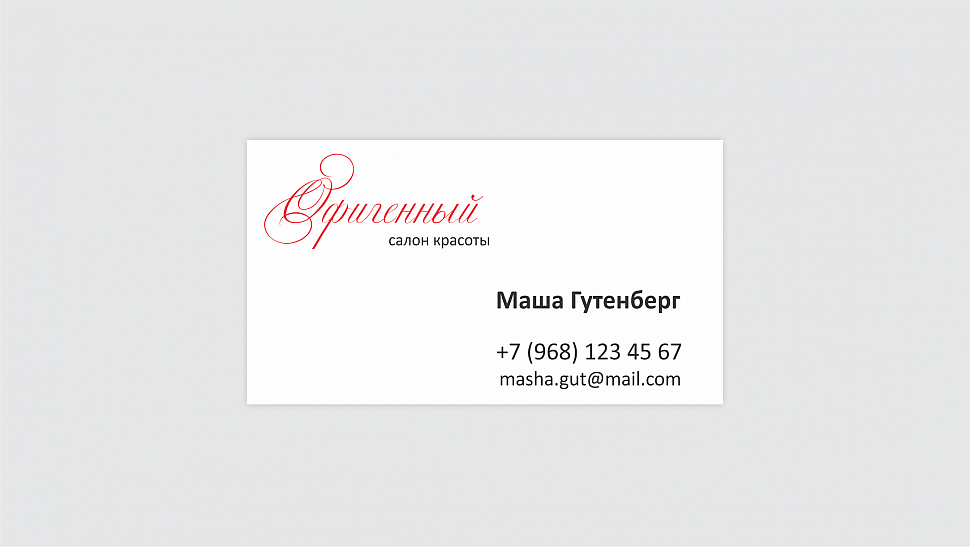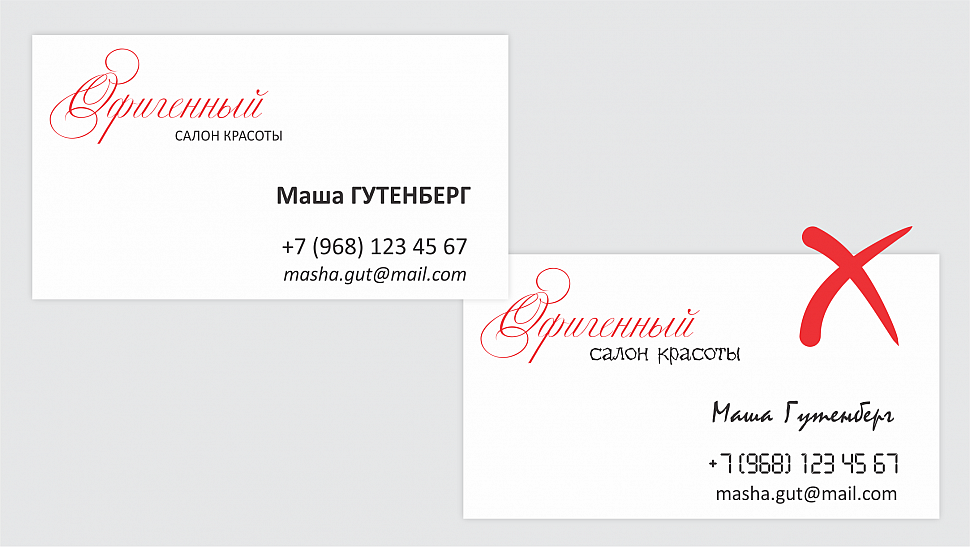
Какой самый лучший шрифт для визитной карточки?
Жаль, но такого шрифта пока ещё не изобрели… Что же делать? Шрифтов – миллионы, а нужный никак не получается найти! Именно поэтому наша типография сделала подборку из самых актуальных шрифтов для визитных карточек на 2019 год, а также полезные советы для того, чтобы выбрать лучший шрифт.
Почему не существует идеального варианта для всех?
Причин много. Разные вкусы, желания и цели. Невозможно соединить все пожелания людей в один шрифт. Для выполнения главной функции визитной карточки (а именно привлечь внимание и сделать уникальной) используются не просто разные шрифта, а в всевозможные комбинации этих шрифтов.
Что нужно знать при выборе шрифта?
- Во-первых, визитка очень мала, поэтому нужно выбирать читабельный, понятный шрифт.
- Во-вторых, нужно выбрать правильный шрифт под материал, который Вы хотите использовать.
Для матовой бумаги советуем более нежные и гладкие шрифты. Для простой – более сдержанные и строгие. - В-третьих, обращайте внимание на свою специфику работы. Если Вы занимаетесь маникюром красиво бы смотрелся шрифт Brusher Cyrillic, Bryndan Write, Caveat и другие подобного плана (резкие, словно быстрый взмах кистью). Для строителей, подрядчиков, сантехников такие шрифты будут явно странными и скорее запутают человека – Вам нужны ровные, строгие и прямые (Bebas Neue Cyrillic, Capture Smallz Clean и прочее).
Подборка полезных 5 шрифтов для визитки на 2019 год
Neuton
Neuton — прекрасный вариант для любителей шрифтов с засечками.
Чем-то напоминает привычный многим, кто когда-то открывал Ворд, шрифт Times. Он компактный в ширину, поэтому можно сэкономить место и он будет хорошо смотреться на экране. Подходит для классической или современной визитки.
Ambarella
Занимаетесь ручной работой? Шьёте, вяжите, создайте дизайн одежды? Гарнитура Ambarella покажет и расскажет это на Вашей визитке. Для настоящих ценителей легкости и красоты. Лучше всего выглядит на матовой бумаге.
Ubuntu
Гарнитура часто используется представителями технологической индустрии, программистами и инженерами. Один из новых шрифтов, представленный в 2010 году.
Alcubierre
Alcubierre — прекрасный вариант для того, чтобы передать легкость и воздушность в дизайне визитки. Аккуратные и мягкие формы, легкие линии делают её уникальной. Помогают людям ощутить «глоток свежего воздуха», глядя на Ваши визитки.![]()
Milkshake
Молодежная, сочная и вкусная гарнитура, которая идеально подходит для визитки и личного резюме. Часто её выбирают кофейни, кондитерские и молодые предприниматели. Буквы жирные и толстые – их легко прочитать и составить ассоциацию с тем же густым и жирным молоком. Похоже на текст, написанный чернильной ручкой. Весьма универсален.
Как выбрать лучший шрифт для визитки
Представьте себе сцену: вы открываете текстовый документ и вводите название своей компании.
На белом фоне оно выглядит мелко, поэтому вы увеличиваете размер до 96. Вы снова произносите название вслух, чтобы услышать, как оно звучит. Это лучший вариант из длинного списка, написанного в вашей записной книжке. Затем вы исследуете меню шрифтов, чтобы увидеть, как оно выглядит в разных стилях букв.
Прежде чем вы это заметите, пройдёт двадцать минут, и вы станете более нерешительным, чем раньше.
Очень. Много. Вариантов.
Ваш бизнес современный и минималистичный или традиционный и элегантный?
Есть тысячи стилей, из которых можно выбирать. Выбор типографского стиля, который будет определять ваш бизнес на следующие несколько лет, представляет собой непростую задачу. Мы надеемся, что эта статья укажет вам правильное направление.
Итак, что такое шрифт?
Шрифт — это набор букв и цифр, акцентов и символов, созданных для единого дизайна. Любые варианты одного и того же дизайна, например, полужирный, обычный или курсив, называются «семейством шрифтов».
Шрифты, которые вы используете на своих визитных карточках, выполняют две основные функции, привлекают внимание и их легко читать.
Имея это в виду, читайте дальше, чтобы узнать больше о типах шрифтов, о том, как комбинировать разные стили и какой размер вы должны сделать для текста на своих визитных карточках.
Типы шрифтов
Что такое шрифт без засечек?
В типографике буквы без засечек не имеют декоративных линий, называемых «засечками», в конце штрихов. Шрифты без засечек также имеют меньше вариаций ширины линии, чем шрифты с засечками (подробнее о них через секунду). В печатной продукции шрифт без засечек лучше всего подходит для названий компаний, заголовков или вывески, поскольку их легко прочитать с первого взгляда. Это также хороший выбор, если вы хотите передать простоту, современность или минимализм.
Шрифты без засечек часто используются для цифрового отображения текста. На дисплеях с низким разрешением мелкие детали, такие как засечки, могут исчезать или казаться слишком большими в зависимости от шрифта.
И на всякий случай, если вам интересно, этот термин происходит от французского слова sans, означающего «без», а «serif», как полагают, происходит от голландского слова schreef, означающего «линия» или штрих пера.
Что такое шрифт с засечками?
Засечки происходят от резных надписей, которые часто встречаются на исторических зданиях, мостах и надгробиях. Эта историческая ассоциация делает буквы с засечками идеальными, если вы хотите создать устоявшийся и традиционный вид. Шрифты с засечками — это наиболее часто используемый стиль в длинных рукописях, книгах, газетах и большинстве журналов. Это связано с традициями, воспринимаемой удобочитаемостью и низким качеством бумаги в прошлом, которые делали оптимальным печать с использованием букв с засечками.
Однако дискуссия о читабельности — спорный вопрос. Один лагерь утверждает, что читаемость и скорость чтения длинных отрывков текста улучшаются, поскольку шрифты с засечками помогают взгляду перемещаться по строке.
Другой лагерь оспаривает это, считая, что буквенный стиль, который мы чаще всего читаем (текст с засечками), легче всего читать.
Помните, что, если вы хотите добавить рельефный глянец к шрифту с засечками на своей визитной карточке, рекомендуется добавлять его только в большое текстовое поле, такое как название вашей компании.
Где использовать рукописные шрифты
Рукописные шрифты — это шрифты, которые передают человеческие прикосновения, такие как плавные курсивные штрихи и соединенные рукописные надписи. Рукописные шрифты отлично подходят для приглашений, поздравительных открыток, заголовков или очень коротких выразительных текстов с личным сообщением. Классические плавные рукописные шрифты создают элегантный вид, а округлые формы создают ощущение удовольствия. Они могут быть эффективными для привлечения внимания, но позаботьтесь о том, чтобы обеспечить их разборчивость, особенно если вы планируете использовать рукописный шрифт для своих вывесок.
Как комбинировать шрифты на визитке
- Сузьте свой выбор до двух шрифтов для своей визитной карточки
- Попробуйте сочетать шрифт script или serif с шрифтом sans-serif
- Создайте визуальную иерархию, решив, какая информация наиболее важна, например, ваша компания или полное имя. Затем определите, какая информация может отображаться в меньшем размере ниже.
- Не обязательно полагаться на размер текста, чтобы добиться визуальной иерархии. Попробуйте использовать жирный шрифт для заметного текста и светлый оттенок для менее заметных текстовых полей.
- Используйте на визитной карточке не более трех размеров шрифта. Два — идеальный вариант. Создайте контраст между текстом и фоном в своем дизайне.
Делайте так, чтобы каждое текстовое поле выделялось. В случае сомнений всегда выделяется черный или темно-серый текст на белом или желтом фоне. - Избегайте сочетания похожих шрифтов. Постарайтесь создать некоторый контраст между названием вашей компании и полем контактных данных.
Размеры шрифта визитной карточки: лучшие практики
В типографике размер пункта (pt) — это стандартная единица измерения, используемая для измерения букв в дизайне. Для заметных текстовых полей визитной карточки, таких как ваша компания или полное имя, размер шрифта может быть от 10 до 16 пунктов в зависимости от того, сколько места у вас доступно. Эти размеры должны отличать основные текстовые поля (наиболее заметные) и второстепенные (менее заметные).
Размер ваших менее заметных текстовых полей, таких как название должности, адрес электронной почты, Интернет, адрес и номер телефона, очень важен с точки зрения видимости и разборчивости. Минимальный размер, который вы должны использовать на наших визитных карточках, — 8 пунктов, но имейте в виду, что некоторые шрифты могут казаться меньше других, даже если оба шрифта имеют одинаковый размер.
Будьте осторожны с рукописными шрифтами и некоторыми засечками небольшого размера. Если вам нужно добавить мелкий шрифт, используйте шрифт без засечек для оптимальной разборчивости.
Помните, что прежде всего текст на визитных карточках должен быть легко читаемым. Как только вы найдете шрифт, который легко читается с первого взгляда, вы можете начать экспериментировать с цветовыми сочетаниями, чтобы выделить свой дизайн.
Визитки — цвет и шрифт | Новости
Создавая визитку, нелишне будет учесть два таких немаловажных аспекта, как цвет и шрифт. Рассмотрим их более подробно:
1) Цвет визитки. Поскольку визитная карточка обладает сравнительно небольшими размерами и при этом предлагает солидный объем информации, то крайне желательно, чтобы визитка представляла собой текст темного цвета на светлом фоне. Если задействуется так называемая выворотка (светлый текст сочетается с темным фоном), то это приводит к уменьшению общего количества текста примерно на треть.
Оформление визитки должно быть максимально строгим, без вычурных завитушек и рамок (это касается в первую очередь деловых визиток; для людей творческих профессий, разумеется, допустимы самые разные варианты). В соответствии с нормами этикета лучше всего заказывать визитки на качественной бумаге высокого качества (очень хорошо, если это дизайнерская коллекция). Не рекомендуется делать поверхность глянцевой – дело в том, что на визитках очень часто оставляют уточняющие пометки, а в этом случае это будет попросту невозможно. В соответствии с нормами этикета подразумевается использование белых, голубых, розовых цветов для фона и черного либо синего цвета для шрифта.
2) Шрифт визитки. Как таковых жестких рекомендаций, связанных со шрифтом, нет – здесь очень многое зависит от сферы деятельности фирмы. В частности, представителям компании, которая предлагает художественную ковку, подойдет готический шрифт с вензелями, подчеркивающий высокое качество изделий ручную работу, их ориентацию на древность и античность.
Напротив, если фирма предлагает современные товары (например, ноутбуки последнего поколения), то здесь будут уместный рубленые шрифты без засечек. Также можно изменять начертание шрифта – например, с помощью жирного шрифта делать акценты на важной информации, а курсивом или тонким шрифтом подчеркивать ювелирное мастерство, сложность работы и изящность товара. Впрочем, не следует забывать об основном правиле – шрифт обязательно должен хорошо читаться. Если визитка читается плохо, то она очень быстро окажется в мусорной корзине. При помощи шрифтов можно правильно расставить акценты (например, выделить несколько большим шрифтом фамилию, имя и отчество владельца). Акценты в визитке, помимо размера шрифта, могут достигаться при помощи форматирования, а также с использованием цветовых наложений на определенные текстовые фрагменты.
Заказать визитки в типографии «Псковское возрождение».
Как должна выглядеть визитка: материал, шрифт, цвет
Визитка — это доступный и простой в изготовлении рекламный материал.
С ее помощью можно распространить информацию о компании или же о конкретном специалисте. Визитные карточки заказывают не только крупные фирмы, но частные мастера, которые работают на себя и оказывают различные услуги (слесари, электрики, программисты и другие).
Такие изделия изготавливается в форме небольшой карточки, которая содержит контактные данные. Важно понять, как должна выглядеть визитка и каким цветом ее оформлять, чтобы она привлекла внимание потенциальных клиентов.
Зачем вам нужны визитки?
Визитки можно использовать для:
Повышения своего статуса в глазах клиента, бизнес-партнера или собеседника.
Рекламы. Изделия хорошо сочетаются с сарафанным радио, так как их можно передавать другим, советуя конкретного специалиста или компанию. Чтобы ваши клиенты с легкостью делились вашими визитными карточками со своими знакомыми, оставляйте им по 2-3 штуки, а не по одной.
Передачи контактных данных. Обычно на карточке указывается номер телефона, электронная почта, контакты в социальных сетях и адрес.
Презентации своих услуг. Можно кратко описать, чем вы занимаетесь.
В зависимости от сферы и условий работы визитки можно использовать по-разному. Они позволяют с минимальными затратами распространить информацию о вас и вашей компании.
Какой должна быть визитка
Почему одна реклама работает, а вторая — никак не способствует росту продаж? Потому что не все маркетинговые стратегии эффективны. Чтобы визитка работала на пользу вашего предприятия, она должна быть односторонней, качественной, стандартной по размеру, лаконичной и легкой в восприятии. Почему именно такие визитки работают лучше других? Об этом поговорим далее.
Двухсторонняя или односторонняя?
Не нужно размещать слишком много информации на небольшом кусочке бумаге.
Это перегружает визитную карточку и мешает восприятию информации. К тому же на односторонних изделиях можно делать заметки с обратной стороны. Потенциальный клиент может записать там время встречи или другие данные, которые будут для него полезными.
Иногда вторая сторона используется для печати информации на иностранном языке: так делать не нужно. Чтобы сделать лучшую визитку для иностранного клиента, нужно заказать небольшой тираж полиграфической продукции на нужном языке.
Размер
Размер должен быть таким, чтобы карточка легко помещалась в кошелек, визитницу или в бизнес-холдер. Стандартный размер такой полиграфической продукции — 90 х 50 или 85 х 55 мм.
Другие размеры и необычные формы позволяют реализовывать нестандартный дизайн, но с использованием таких визиток могут возникнуть проблемы. Если они не будут помещаться в портмоне, они будут лежать без дела и очень быстро потеряются.
Стандартные прямоугольные визитки работают лучше, чем другие карточки.
Выбор материала
Материал, на который наносится текст и логотип, должен быть плотным. Если карточка будет сделана из тонкой бумаги, она быстро порвется и помнется. Бумага с тиснением — не самый лучший вариант, так как на ней неудобно делать пометки. Разные декоративные элементы (глянец, тиснение и прочее) лучше всего использовать для тех изделий, которые раздаются как рекламные листовки.
Чаще всего для изготовления визиток используется:
На такой материал можно наносить разные оттенки с хорошей цветопередачей и реализовывать необычные идеи с градиентом, линиями и другими элементами. Также учитывайте, что матовые карточки смотрятся строже и сдержаннее, чем глянцевые.
Какой цвет лучше для визитки
Для фона визитки нужно подобрать такой цвет, который не будет отталкивать, мешать восприятию информации и будет дополнять концепцию бренда. На какие оттенки стоит обратить внимание:
Красный цвет ассоциируется с рекламой, модой и шоу-бизнесом.
Этот оттенок используют компании, которые занимаются организацией праздников, а также фотографы, декораторы и многие другие.
Зеленый часто применяется в образовательной сфере, культуре и искусстве. Этот оттенок выбирают компании, работа которых связана с экологией.
Металлические цвета (белый, серый, серебристый) отлично подходят для финансовых компаний, автосервисов, специалистов по продажам и для организаций, которые занимаются ремонтом техники и электроники.
Черный и голубой оттенки позволяют воплотить многие идеи, связанные с технологией, информацией, туризмом, развлечениями и сферой услуг. Например, в этих цветах можно сделать визитку аквапарка.
Коричневый и желтый оттенки ассоциируются с документами, поэтому их часто используют специалисты, чья деятельность связана со строительством, торговлей и недвижимостью.
Чтобы решить, какого цвета сделать визитку, достаточно рассмотреть несколько вариантов. Дизайнеры рекламно-производственной компании CreativePRO отходят от стандартных решений и предлагают на выбор несколько интересных дизайн-макетов. Каждый дизайн продумывается в индивидуальном порядке.
Выбор шрифта
Чтобы понять, какой шрифт выбрать для визиток, нужно определиться с общей концепцией. Каллиграфические элементы смотрятся красиво, но они плохо влияют на читабельность текста. Универсальное решение — простой шрифт со средним межбуквенным интервалом.
Также шрифты для визиток бывают:
рукописными — их не всегда легко разобрать, поэтому стоит использовать только там, где они будут уместными;
художественными — авторские решения для творческих компаний;
с засечками — короткими перпендикулярными штрихами на буквах;
с тонкими буквами;
с широкими элементами букв.
Специалисты CreativePRO предложат вам несколько вариантов шрифтов на выбор, учитывая стиль дизайн-макета. Надписи должны быть читабельными и не громоздкими. Наши дизайнеры знают, как эффективнее всего презентовать информацию о ваших услугах на визитке.
Какая информация должна быть на визитке
На визитке обязательно должны быть указаны имя и фамилия специалиста, его контакты и контакты фирмы, в которой он работает. Сложные рисунки и ненужная информация могут сместить акцент на себя, усложнив восприятие. Также можно добавить краткий перечень основных услуг. Если у фирмы есть логотип, его обязательно стоит использовать при создании дизайн-макета визитной карточки.
Не перегружайте изделия лишней информацией, если вы работаете в разных сферах. Лучше закажите в CreativePRO несколько вариантов карточек для разных ситуаций. Такое решение подходит для тех фирм, которые специализируются на предоставлении различных услуг.
Например, если вы преподаете английский, а в свободное время делаете торты на заказ, вам стоит сделать две визитные карточки.
Выбирать дизайн для визиток нужно внимательно, учитывая все тонкости их дальнейшего использования. Вы также можете заказать маркетинговое исследование, чтобы наши специалисты изучили рынок предложений в вашей сфере и подобрали лучшие идеи для рекламы. Визитки — это один из самых доступных способов для реализации таких идей.
Статьи | Рекламное агентство АВТ Центр
Азы технологии блокчейн
Представляем вашему вниманию выдержки из статей IBM на тему революционной технологии блокчейн (blockchain). Все мировое сообщество делает ставки на то, насколько кардинально технология блокчейн изменит способы осуществления организациями своих финансовых операций. Давайте разберемся, как работает сеть блокчейн, что делает ее уникальной и как IBM помогает ее совершенствовать. Для начала небольшая предыстория.
технология блокчейн
Битрикс24. Презентация 2017
Битрикс24: Полный комплект инструментов для организации работы компании.
Презентация новой версии Битрикс24 «Сингапур» — Общайтесь и принимайте решения. Быстро и легко.
битрикс24 bitrix24
Сравнение редакций 1С-Битрикс: Управление сайтом
Программный продукт «1С-Битрикс: Управление сайтом» включает шесть редакций, различающихся по функциональным возможностям: от управления контентом сайта до создания портальных интернет-решений для электронной торговли.
Сравните редакции по функциональным возможностям и комплектации интернет-магазина. |
bitrix разработка сайта
Композитный сайт
Уникальная технология производства сайтов объединяет в себе высокую скорость загрузки статического сайта и все возможности динамического сайта.
Пользователь мгновенно получает контент страницы.
bitrix разработка сайта
Возможности CMS 1С-Битрикс для SEО для маркетинга
Функционал Битрикс, позволяет решать многие задачи по SEO оптимизации, а так же предоставляет ряд маркетинговых профессиональных инструментов для анализа конверсии, прогнозирования рентабельности сайта, для автоматической работы с контекстной рекламой (максимальная выгода, при минимальной ручной коррекции). Битрикс постоянно развивается и улучшает качество и разнообразие маркетинговых модулей, состав которых различается в зависимости от редакций.
bitrix реклама маркетинг
Возможности CMS 1С-Битрикс для SEО оптимизации
SEО функционал Битрикс, позволяет решать многие задачи по внутренней оптимизации, не только профессионалам, но и пользователям сайта.
Чтобы менеджер CMS 1С-Битрикс мог самостоятельно, на базовом уровне, настроить на своем сайте поисковую оптимизацию, Битрикс встроил в CMS ряд простых в применении решений, позволяющих создавать сайты дружественные к поисковикам.
bitrix
Forbes: 5 типичных ошибок при продвижении стартапов
Начиная работать над стартапом, молодой предприниматель сталкивается с огромным количеством задач и проблем. Справившись с первым «ворохом задач» и находясь в эйфории от факта создания бизнеса, бизнесмен со рвением принимается за Продвижение своего бизнеса… и тут же наступает на очередные грабли. Предлагаем список из 5-ти вопросов, которые обязательно нужно сформулировать для себя лично, начиная продвигать стартап.
ошибки стартапа продвижение стартап продвижение стартапа
Dofollow и Nofollow: что за зверь и с чем его едят?
Параметры DoFollow и NoFollow тега a href используются для указания поисковым роботам, как поступать со встреченной в тексте ссылкой.
Они определяют следует роботу уходить по данной ссылке на поисковую индексацию указанной страницы или нет. В кодировании задание этих параметров выглядит следующим образом:
сео оптимизация
Источник креативности и интеллекта
Специалисты из Университета Южной Калифорнии провели любопытное исследование. Их целью было выяснить, какие зоны мозга активны, когда человеку нужно проявить креативность. В этой части своей работы ученые исследовали реакцию на визуальные задания с помощью функциональной МРТ. В эксперименте участвовали студенты архитектурного факультета. Им предложены были следующие фигуры: круг, буква С и цифра 8. Сначала молодых людей попросили представить изображения, которые содержали бы все предложенные фигуры. Например, лицо, состоящее из круга, восьмерки в качестве глаз и буквы С в виде улыбки. Возможны и другие варианты. Это задание требует от человека нестандартного подхода и взгляда на вещи, т.
е. именно того, что называют креативностью. Затем студентов попросили мысленно соединить фигуры вместе. Для этого требуется пространственное мышление, которым, конечно, должны обладать студенты архитектурного факультета. А вот креативность для этого не требуется.
интересные факты исследования
10 типичных ошибок начинающих предпринимателей
Статья Стива Павлина о наиболее частых ошибках начинающих предпринимателей, и о том как их избегать: 1. Продажи не тем людям… Научитесь говорить «нет» слабым предложениям 2. Слишком большие траты. В эпоху Интернета вы можете легко запустить бизнес на… 3.Чрезмерная скупость — это…
Стив Павлина, основатель и исполнительный директор Dexterity Software. Разработчик ПО, популярный создатель компьютерной игры Dweep, американский писатель, автор книг по саморазвитию, рассказал, что за 14 лет, в течение которых он занимается собственным бизнесом, он допустил немало ошибок.
Перечисляя наиболее частые ошибки начинающих предпринимателей, он говорит о том, как их следует избегать.
ошибки стартапа продвижение стартапа
App Store: Дизайнер Визиток
Самый простой способ создать профессиональную визитную карточку, даже если у вас есть нулевой дизайн! В течение нескольких минут вы можете создать визитную карточку, которая представит профессиональный и незабываемый образ себя и вашего бизнеса. Приложение Business Card Maker заполнено множеством бесплатных ресурсов, включая шаблоны, шрифты и значки, которые вы можете изменить так, как хотите. Нужен дизайн, подходящий для вашего бизнеса, промышленности и личного стиля? Вы найдете его. Загрузите готовый к печати файл с высоким разрешением бесплатно, без трюков или водяных знаков.
Кроме того, приложение Конструктор визиток (Business Card Maker) поставляется с функциональностью Desygner, как описано Forbes, Product Hunt, Social Media Examiner, Entrepreneur и Terra.
Присоединитесь к 4 миллионам + людям, которые используют Desygner для создания красивого контента быстро и бесплатно.
СОЗДАТЬ ЛЕГКО: ВСЕ мощные и простые в использовании инструменты редактирования, которые вам нужны, такие как изменение размера, изменение шрифта, изменение цвета, выравнивание, порядок слоев и многое другое. Редактируйте изображения, текст и значки любым способом.
БЕСПЛАТНЫЕ ИЗОБРАЖЕНИЯ, ИКОНЫ И ШРИФТЫ: больше не платите за такие пакеты, как другие приложения, иногда до 10 долларов за изображение или значок. Конструктор визиток (Business Card Maker) приложение поставляется с бесплатным контентом без забот о лицензиях!
ИМПОРТ СВОИХ СОБСТВЕННЫХ ИЗОБРАЖЕНИЙ: добавьте контент из рулона камеры, социальных сетей и накопителей.
СКАЧАТЬ БЕСПЛАТНО БЕСПЛАТНО! Все, что вы создаете с помощью приложения Конструктор визиток (Business Card Maker), принадлежит вам, как вы пожелаете.
– SHARE разрабатывает электронную почту, Instagram, Facebook, Twitter и многое другое.
– СКАЧАТЬ как JPEG, PNG или PDF.
– ПЕЧАТЬ с вашего телефона за считанные секунды.
AUTOMAGICALLY RESIZE: вам не нужно обновлять, чтобы изменить размер и перераспределить Визитные карточки. Измените размер файлов столько раз, сколько хотите.
ВОССТАНОВИТЬ ПРЕДЫДУЩИЕ ВЕРСИИ: «Хм … Думаю, вчера это выглядело лучше». Не беспокойтесь, просто получите доступ и верните лучшую версию своих Визитные карточки.
МАГАЗИН И РЕДАКТИРОВАТЬ В ЛЮБОЕ ВРЕМЯ: Создайте столько Визитные карточки сколько хотите, и сохраните их бесплатно. Они всегда будут доступны для редактирования с вашего компьютера и мобильного устройства с вашей учетной записью Desygner.
Если вы хотите перевести свой Визитные карточки на совершенно новый уровень, вам может понравиться подписка PRO. За $ 19,99 USD / год (или единовременный взнос в размере 29,99 долларов США за пожизненный доступ) вы откроете все про шаблоны, получите доступ к 800 + Royalty-Fonts шрифтам, ищите изображения без ограничений и наслаждайтесь без рекламы.
Цена подписки может разниться в других странах.
Годовая подписка PRO автоматически возобновляется, и взимается с вашей учетной записи iTunes на ту же сумму в течение 24 часов до конца текущего периода. Плата будет автоматически снята по окончании пробного периода, если вы не отмените его ранее. Автоматическое обновление может быть отключено в любое время, перейдя в настройки iTunes Store после покупки. Любая неиспользованная часть бесплатного пробного периода будет утеряна после покупки. Покупка пожизненного доступа позволяет вам получить доступ к сервисам Pro, до тех пор, пока эти услуги доступны. Мы не даем никаких гарантий или заявлений о том, что любые из услуг будет доступны в течение любого периода времени, и вы признаете и соглашаетесь с тем, что услуги могут меняться или прекращаться в любое время в будущем. Для получения более подробной информации ознакомьтесь с условиями и правилами конфиденциальности.
Популярные ошибки в дизайне визиток
Иногда макеты для визиток разрабатывают не компетентные в таких вопросах люди либо их вообще выполняют без каких-либо навыков самостоятельно, используя шаблоны, полученные в интернете.
После того, как не знающий правила дизайна и вёрстки человек приступает к заполнению шаблона, он иногда «перегибает» с креативными элементами и делает визитку нечитаемой. Для облегчения считывания контактов и эффективного донесения информации до сознания требуется избегание распространённых ошибок.
Подать заявку на ватсап С мобильного — Жмите на ссылку и будет переход на ватсап.>>> ПОДАТЬ ЗАЯВКУ НА ВАТСАП
Рассмотрим наиболее популярные из них.
- Избыток дизайнерских приёмов. Чтобы избежать этого, нужно придерживаться умеренности при использовании украшений, указывая исключительно важные данные и не используя яркие цвета. Лучше поменьше и более сдержанно, чем побольше и напыщенно — таков главный принцип, которому должна следовать деловая полиграфия.
- Вычурные шрифты, которые не сочетаются между собой. Стремясь выделиться, некоторые используют шрифты, слишком трудные для восприятия. Некоторые даже каждое предложение пишут отдельным шрифтом, создавая смесь букв разного формата, крайне сложную для понимания.
Во избежание этой ошибки нужно выбирать не более двух различных шрифтов, причём желательно предпочитать распространённые виды. Поразить воображение не получится, однако их легко считывать. Всё же лучше, чтобы шрифт особо не выделялся, поскольку главное — содержание текста. - Ошибки при указании контактов. Простейшая стильная визитка может содержать досадную ошибку — неудобное указание ссылки либо ника. По этой причине необходимо предварительно позаботиться о соответствии почтового домена домену сайта, при этом ID в социальной сети должен состоять не из цифро-буквенного набора, а иметь вид фамилии либо бренда. Одна из ошибок — написание сплошь рядом цифр номера телефона: код страны и код города должны оформляться в скобках, сам же номер нужно писать раздельно с чёрточками либо пробелами для лёгкого прочтения и набора.
Наша типография в Новосибирске «Идеал Принт» осуществляет печать визиток высокого качества. Мы — команда настоящих профессионалов. Наша полиграфия без ошибок и брака создаёт визитки двусторонние и односторонние.
Визитки, которые действуют по-настоящему эффективно.
Вы можете позвонить нам прямо сейчас по одному из телефонов: +7 (383) 346-02-75 +7 (383) 292-25-82
+7 (383) 335-71-18 или отправить сообщение прямо с сайта
Лучший шрифт для визитных карточек
Технология полностью изменила методы работы компаний в 21 веке.
И все же такая, казалось бы, простая вещь, как визитные карточки, выдержала испытание временем и остается неотъемлемой частью любого серьезного профессионала, который хочет наладить контакт с потенциальными клиентами или партнерами.
Но создать эффективную визитную карточку непросто. С очень небольшим пространством для передачи того, что вы представляете, даже мельчайшие детали играют жизненно важную роль.И выбор лучшего шрифта для визитных карточек не является исключением.
Но какое значение имеют шрифты визитных карточек? И какие из лучших шрифтов для визитных карточек вы должны рассмотреть?
Давайте ответим на важные вопросы ниже.
Средний размер визитных карточек в Соединенных Штатах составляет всего 3,5 x 2 дюйма, что оставляет очень мало места для творчества или сложного дизайна. В большинстве случаев вы можете выбрать только тип логотипа, который вы используете, копию, которую вы используете, бумагу, на которой вы хотите печатать, и шрифт, которым вы хотите, чтобы карта была написана.
Несмотря на то, что в визитной карточке содержится всего несколько переменных, существует бесчисленное множество примеров того, как их можно использовать по-разному. Деловые шрифты находятся в самом центре того, чтобы сделать это возможным.
Выбрав правильный размер и тип шрифта визитной карточки, вы можете сделать свое сообщение заметным и привлечь внимание, а также изобразить себя как профессионала, что имеет решающее значение, если визитка будет эффективно служить своей цели.
Лучший размер шрифта для визитных карточекВыбор шрифта вашей визитной карточки находится в самом центре дизайна, но как вы должны подходить к выбору?
У вас может возникнуть соблазн выбрать меньший размер шрифта для визитных карточек, чтобы получить больше информации о карточке, но это часто является ошибкой.
Чтобы информация была полезной, люди должны ее прочитать, и мало кто из ваших потенциальных клиентов будет напрягать глаза и щуриться, пытаясь расшифровать крохотные буквы, если вы нажмете слишком мелко.
В то же время вам не следует выбирать слишком крупный шрифт — если только он не является частью хорошо продуманного дизайна — потому что вы не сможете предоставить основную информацию.
В идеале вы должны выбрать размер шрифта 10-11 pt для основной части текста и можете сделать его немного меньше для контактной информации, если вам не хватает места.
Лучшие профессиональные шрифтыШрифт — это больше, чем просто стиль слов на вашей карточке. Это также представление о вас как о профессионале и о том, как вы хотите себя позиционировать.
Если вы хотите передать профессиональное сообщение, рекомендуется выбрать шрифт, выдержавший испытание временем, как часть дизайна визитной карточки. Три самых традиционных и проверенных временем шрифта:
- Helvetica
- Times New Roman
- Arial
Эти шрифты идеально подходят для деловых целей: они легко читаются и узнаваемы.
Однако, если вы рассматриваете лучшие шрифты для визитных карточек, чтобы сделать текст вашей визитной карточки запоминающимся, вы можете рассмотреть менее распространенный, но столь же профессиональный выбор шрифта.
Чтобы выбрать идеальный, уникальный шрифт для визитных карточек, первое, что нужно учитывать, — это тип вашей работы с засечками или без засечек. Шрифты с засечками классические, литературные и легко читаемые. Они широко используются в издательском деле. Из трех перечисленных выше шрифтов Times New Roman является единственным шрифтом с засечками.Вот еще несколько идей шрифтов с засечками, которые передают вневременной класс:
- Baskerville
- Palantino
- Bookman Old Style
- Century
- Georgia
С другой стороны, если ваш бизнес стильный, современный и минималистичный, вы можете предпочесть четкий шрифт без засечек. Без засечек просто означает, что буквы не имеют засечек. Другими словами, к основным штрихам каждой буквы не добавляются дополнительные линии или штрихи.
Arial и Helvetica — это шрифты без засечек. Если вы ищете шрифт без засечек, такой же профессиональный, как Helvetica или Arial, но немного менее распространенный, вот несколько советов для размышления:
- Futura
- Avant Garde
- Optima
- Droid Sans
- Roboto
Хотя некоторые из лучших бизнес-шрифтов являются профессиональными и вневременными, они могут не подходить для каждой ситуации, особенно для профессий, требующих демонстрации творчества и уникального чувства стиля.
Например, если ваша визитная карточка должна отражать ваш опыт в области дизайна, фотографии или изобразительного искусства, лучший шрифт для вашей визитной карточки должен быть более выразительным и смелым, дополняя креативность вашего личного бренда.
Вот несколько наших лучших предложений по креативным шрифтам для визитных карточек:
- Emberly
- Saint George
- Author Type
- Bouquet
- High Life
Креативные шрифты, как правило, немного более необычны и сильно различаются.
В зависимости от вашего бизнеса вы можете выбрать шрифт, который выглядит как мазки, например Author Type, модный шрифт, например Emerly, или элегантный рукописный шрифт, например Bouquet. В любом случае, помните, что ваше сообщение должно быть четким и разборчивым.
При выборе шрифта подумайте о том, что вы представляете и какой бренд вы хотите развивать: это сыграет важную роль при выборе шрифта. В конце концов, как только вы сделаете выбор, шрифт станет частью вашей профессиональной идентичности.Это будет одна из первых вещей, с которыми люди столкнутся, когда узнают о том, чем вы занимаетесь.
Независимо от того, выбираете ли вы классический шрифт или современный, помните, что функция визитной карточки остается неизменной. Он должен передавать важную информацию, но он также должен быть достаточно привлекательным, чтобы привлечь внимание.
Вы даже можете обнаружить, что несколько различных шрифтов идеально дополняют друг друга для различных разделов вашей визитной карточки, поэтому не настраивайтесь на использование только одного.
При таком небольшом количестве переменных каждый компонент, включая шрифт, играет гораздо более важную роль. Итак, каких ошибок следует избегать при выборе шрифта?
Прежде всего убедитесь, что вы стремитесь к удобочитаемости и пониманию. Вы можете использовать бесчисленное количество умных способов структурировать свою визитную карточку, но убедитесь, что они не усложняют чтение и не затрудняют понимание основного сообщения.
Не стесняйтесь использовать мелкие детали, чтобы добавить уникальности, но не переусердствуйте, так как это только превратит их в отвлечение, которое снизит вероятность того, что ваша визитная карточка будет служить своей основной цели.
Сопоставление нескольких шрифтов допустимо, но будьте осторожны, чтобы не создать диссонанс на вашей карте. Если вы не уверены в стилистическом выборе или опасаетесь ошибиться, подумайте о том, чтобы проконсультироваться со специалистами по печати, которые могут предложить помощь.
Дизайн визитных карточек — это вид искусства, который постоянно совершенствовался на протяжении веков.Крайне важно следовать лучшим практикам, которые были разработаны, чтобы гарантировать, что ваши усилия не пропадут даром. В Printivity мы помогли бесчисленному количеству клиентов найти идеальный дизайн и лучший шрифт для визитных карточек в их ситуации. Мы можем предложить вам полный пакет рекомендаций, который обеспечит наилучшие результаты. Если вы хотите узнать больше о наших визитных карточках или других услугах, включая срочную печать за ночь, позвоните нам по телефону 1-877-649-5463 или воспользуйтесь нашей контактной формой. !
15 простых шрифтов для визитных карточек, которые обычно используют профессионалы — Блог GotPrint
Выбор шрифта является одним из наиболее важных элементов дизайна, который отражает мастерство дизайнера, участвующего в любом дизайн-проекте.Выбор шрифта — это не только размер шрифта, цвет или разборчивость.
Вместо этого шрифт задает тон всей визитной карточке. Правильный шрифт четко передает ваше сообщение и органично сочетается с остальным дизайном карты.
всегда должны соответствовать дизайну и целевой аудитории, поэтому важно иметь в своем распоряжении целый арсенал потрясающих шрифтов для различных проектов. Вот коллекция из 15 простых, но профессиональных шрифтов, подходящих для визитных карточек.
Источник изображения: MyFonts
1.Гельветика
Helvetica не просто так является классикой и остается лучшим выбором, когда речь идет о визитных карточках. Helvetica проста, но не скучна. Шрифт Grotesque без засечек был первоначально разработан в Швейцарии в 1957 году и быстро заменил Futura как самый популярный шрифт без засечек в мире.
Графический дизайнер Дикран К. объясняет: «Мой любимый шрифт — Helvetica. Некоторые шрифты имеют настолько сильную индивидуальность, что определяют общий дизайн. Helvetica, на мой взгляд, больше, чем шрифт, это инструмент дизайна, формы букв идеально обработаны и приятны для глаз.
Это вневременной шрифт».
2. KG Извините, не извините
Источник изображения: MyFonts
Когда дело доходит до вашей визитной карточки, вы хотите, чтобы ваше имя выделялось. KG «Извините, а не извините» был разработан, чтобы выделиться в профессиональном плане. Дизайнер Кимберли Гесвейн описывает шрифт следующим образом: «Это чистый шрифт с заглавными буквами, который отлично подходит для имен».
KG «Извините, но не извиняйтесь» легко читается с непринужденной атмосферой, поэтому это отличный выбор для пользователей, которые хотят, чтобы их визитные карточки выглядели как диалоги.
3. Рислинг
Источник изображения: Font Squirrel
Шрифт «Рислинг» вневременной, гладкий и элегантный, как и классическое вино, в честь которого он назван. По словам дизайнера Эвиана, «мне нравится деликатность шрифта и преувеличенный выносной элемент. Шрифт очень стилизован, линии переходят от толстых к тонким, а отслеживание очень точное и чистое с оттенком игривости».
Рислинг придает европейский оттенок любому дизайну, и он обязательно выделится на любой визитной карточке, не чувствуя себя слишком эффектно.
4. Gibson
Источник изображения: MyFonts
Gibson продолжает оставаться популярным среди дизайнеров по уважительной причине. Он предлагает легко читаемый шрифт без засечек, созданный знаменитым канадским шрифтовым дизайнером Родом Макдональдом.
5. Цитадель
Источник изображения: Fonts.com
Во многих случаях лучше меньше, а отличительной чертой Ciutadella является ее простота. Чистый внешний вид шрифта идеально вписывается в различные стили дизайна.Создатель Эдуардо Мансо разработал этот геометрический шрифт без засечек, чтобы он был простым, но не скучным.
6. Centrale Sans
Источник изображения: MyFonts
Если вы ищете открытый шрифт с современным оформлением для своей визитной карточки, вы не ошибетесь с Centrale Sans.
Этот теплый, дружелюбный шрифт профессионален, но не кажется скучным.
7. Бесконечность
Источник изображения: Behance
Как следует из названия, этот шрифт предлагает бесконечное количество возможностей.Infinity легко читается с уникальным современным оттенком. Когда вы используете этот шрифт на своей визитной карточке, вы оцените его простые линии и изгибы.
8. Садовый гном
Источник изображения: Fonts.com
Этот округлый, упругий шрифт имеет причудливый вид. Благодаря своему веселому стилю это отличный выбор для визитных карточек для тех, кто занимается детьми, таких как авторы детских книг, учителя или другие специалисты.
9. Кэмптон
Источник изображения: Behance
Заявите о себе с помощью этого нетрадиционного геометрического шрифта.Ваше имя обязательно будет выделяться на вашей визитной карточке, если вы добавите современный штрих с помощью Campton.
Шрифт включает штрихи от Johnston Sans и Gills Sans с современным оттенком.
10. Яапокки
Источник изображения: Behance
Очарование старого мира и современные четкие линии встречаются в семействе шрифтов Jaapokki. Шрифт чистый и хорошо сбалансированный, что делает его отличным выбором для визитных карточек и других печатных проектов. Лучше всего то, что Jaapokki, две альтернативы и большой набор глифов доступны бесплатно для пользователей по всему миру.
11. Nexa
Источник изображения: MyFonts
Когда вы создаете визитную карточку, вы хотите убедиться, что ваше сообщение и контактная информация переданы четко. Nexa предлагает отличную читаемость благодаря чистым линиям и сдержанной элегантности. Семейство шрифтов Nexa включает 16 различных стилей и начертаний, поэтому вы можете разнообразить свою визитную карточку, сохраняя преемственность между стилями Nexa.
12. Траян
Источник изображения: MyFonts
Придайте нотку классического стиля своему следующему дизайну визитных карточек, включив Trajan.
Этот шрифт был вдохновлен классическими римскими буквами. Сдержанная элегантность Trajan помогает выделить вашу визитную карточку из толпы, оставаясь при этом профессиональным.
13. Futura®
Источник изображения: MyFonts
Future был впервые представлен компанией Bauer Type Foundry в 1928 году, и этот классический шрифт выдержал испытание временем. Дизайнеры ценят большой межстрочный интервал и широкий выбор весов и стилей, а зрители сразу замечают силу и ясность Futura.
14. КОД
Источник изображения: MyFonts
CODE включает в себя многие детали традиционных шрифтов без засечек и добавляет современный вид. Дизайнеры описывают этот шрифт с заглавными буквами как чистый и элегантный, и читатели ценят его прямолинейность.
15. Невис
Источник изображения: TenByTwenty
Если вы хотите, чтобы информация на вашей визитной карточке выделялась, Невис — отличный выбор.
Этот сильный шрифт отличается сильными углами и особенно привлекает внимание, когда используется для всех заглавных букв.Используйте его, чтобы подчеркнуть свое имя на визитной карточке, когда вам нужно изобразить сильного, но дружелюбного человека.
В следующий раз, когда вы будете искать вдохновение для шрифта для визитной карточки, просмотр этих вариантов — отличное место для начала. Подумайте о сообщении, которое вы хотите отобразить, и проверьте, подходит ли какой-либо из этих шрифтов для ваших нужд.
В дополнение к этим 15 вариантам для современных дизайнеров доступно множество других замечательных шрифтов. Как вы сужаете варианты шрифтов? Какой ваш любимый шрифт для визитных карточек? Мы хотели бы услышать ваши идеи ниже!
Статья Лорейн Ф.
хороших шрифтов для визиток | Малый бизнес
При разработке визитной карточки для малого бизнеса вы должны сбалансировать две противоречащие друг другу цели: выделиться и соответствовать. в соответствии с деловыми ожиданиями ваших клиентов.
Выбранный вами шрифт во многом способствует восприятию уникальности и профессионализма.
Helvetica
Helvetica обеспечивает отличную читаемость.Тем не менее, он очень часто используется. Попробуйте варианты в семействе Helvetica, такие как Helvetica Neue в светлом, стандартном и курсивном стилях. Не бойтесь использовать обычную Helvetica для своей контактной информации, потому что это единственное место, где вам нужна абсолютная ясность.
Myriad Pro
Myriad Pro предлагает высокую читабельность с небольшим чутьем. Закругленные хвостики букв «y» и «j» придают стильный вид, а чистый вид заглавных букв говорит об аккуратности и профессионализме.Этот шрифт представлен в нескольких стилях, включая расширенный, светлый и полужирный.
Glasgow
Glasgow предлагает некоторые формальности шрифта Times Roman с обновленным внешним видом. Строчная буква «g» является формальной, а прописные буквы предлагают аналогичную формальность. Жирная версия этого шрифта очень толстая, что делает меньшие размеры, используемые на визитных карточках, очень читабельными.
Karat
Karat предлагает игривую формальность. Изогнутые буквы выглядят немного мультяшными, но прямые линии четкие и обрезаны под углом на концах, чтобы создать ощущение движения.
Размер
По данным BusinessKnowHow.com, одной из основных ошибок является выбор слишком маленького размера шрифта. Визитные карточки очень маленькие, и вы можете потратить много времени на выбор правильного шрифта, только чтобы подорвать свои усилия, выбрав этот шрифт небольшого размера. Как только вы наберете всего 6 баллов, у ваших зрителей возникнут проблемы с чтением.
Смешивание шрифтов
Вы можете смешивать шрифты на своей визитной карточке. Выберите необычный, но читаемый шрифт для названия вашей компании, а затем выберите простой Ariel или Helvetica для контактной информации.Обратите особое внимание на то, как выглядят номера, потому что вы хотите, чтобы ваш клиент мог позвонить вам.
Руководство по стилю шрифтов для визитных карточек
Решили, что вам нужны визитные карточки для распространения информации о вашей работе, но не знаете, какие визитки лучше всего подходят для вашей отрасли?
В этом руководстве мы рассмотрим все, что можно и чего нельзя делать, когда дело доходит до выбора правильного стиля и шрифта.
Выбор правильного шрифта для визитной карточки — это то, чем часто пренебрегают — это может оказать огромное влияние на то, каким будет ваш бизнес-автомобиль.
В зависимости от типа бизнеса шрифт имеет решающее значение для передачи основного сообщения вашей компании. Ищете ли вы традиционные шрифты для более профессионального вида или более игривый шрифт, чтобы понравиться вашим клиентам.
Визитная карточка может быть первым, что кто-то увидит в вашей компании, поэтому чрезвычайно важно произвести хорошее первое впечатление. Слишком жирный и броский шрифт может кого-то оттолкнуть, а если шрифт не бросится в глаза, то он не запомнится.
Что искать в шрифтах визитных карточек Прежде чем выбрать шрифт, которым вы хотите представить свой бизнес, вам нужно подумать о том, что вы продаете. Если, например, вы продвигаете художественную галерею, вы можете выбрать более стильный и причудливый шрифт.
Возможно, вы владеете сантехническим бизнесом, и в этом случае вы бы выбрали четкий и профессиональный шрифт. Есть несколько вещей, о которых нужно подумать, когда дело доходит до выбора лучшего шрифта для вас.
ЧитаемостьУдобочитаемость, пожалуй, самый важный фактор при создании хорошей визитной карточки. Крайне важно получить лучший размер и стиль шрифта. Никто не хочет щуриться, пытаясь прочитать крошечный шрифт. Еще хуже шрифт, который затрудняет понимание слов.
Прежде всего, вы должны уметь читать визитную карточку с первого взгляда и понимать, что рекламируется. Он должен быть простым, но достаточно привлекательным, чтобы кто-то посмотрел дважды.
Полужирный или более крупный шрифт полезен, так как он с большей вероятностью останется в памяти. Выделение ключевых слов жирным шрифтом — отличная стратегия для привлечения внимания к таким вещам, как ваше имя или основная рекламируемая услуга.
Привлекательный внешний вид Хорошая визитная карточка должна быть привлекательной для покупателя.
Это зависит от бизнеса — один и тот же шрифт может быть привлекательным для одной компании и отталкивающим для другой.
Хорошим примером этого может быть визитная карточка строительной компании.Смелый традиционный шрифт, который передает силу и надежность, идеально подходит для этой отрасли. Это дает ощущение силы и профессионализма, что привлекает клиентов, ищущих этот тип работы.
Тот же шрифт и стиль не будут иметь такого же эффекта для визитной карточки семейного ресторана. Вместо этого он будет излучать холодную враждебность, которая, скорее всего, оттолкнет людей.
Отражает ваш брендВажно отметить, что шрифты визитных карточек будут представлять вашу компанию и услуги, в отличие от веб-сайтов или листовок, которые могут менять шрифт в зависимости от написанного контента.Это делает критически важным, чтобы вы прибили его к голове, когда дело доходит до выбора шрифта, отражающего ваш бренд.
Шрифты способны выражать широкий спектр эмоций у тех, кто их читает.
Классические шрифты, такие как Times New Roman, Helvetica и Arial, хороши для традиционных компаний. Они дают ощущение профессионализма и вызывают доверие у клиента.
Если ваш бренд фокусируется на творчестве и приятном времяпрепровождении, выберите шрифт, представляющий это! Никто не запишется на художественный урок, если карточка, рекламирующая его, скучна.Это должно быть весело и необычно, как и предлагаемая вами услуга.
Лучшие шрифты для визитных карточекХорошая визитная карточка — это больше, чем просто способ предоставления контактной информации. Он знакомит вас с типом бизнеса, которым вы управляете, и с тем, чем вы отличаетесь от остальных. Шрифт играет ключевую роль в донесении этого сообщения.
Между стилями шрифтов есть несколько ключевых различий. Существуют шрифты без засечек, шрифты с засечками и рукописные шрифты. Шрифты без засечек описываются как современные, приветливые и четкие.Шрифт с засечками дает ощущение профессионализма и доверия, тогда как рукописные шрифты более индивидуальны.
Здесь мы перечислили некоторые из лучших шрифтов для визитных карточек и некоторые преимущества каждого стиля. От более простых шрифтов, таких как Helvetica, до более причудливых шрифтов, таких как Kensington.
ГельветикаHelvetica доказывает силу простоты. Это классический шрифт, который легко читается, но при этом не слишком громоздкий. Его можно использовать для представления широкого круга предприятий, что делает его идеальным шрифтом для тех, кто не хочет слишком много экспериментировать.
АриалArial — еще один бесплатный шрифт, похожий на Helvetica в отношении простоты. Основное отличие заключается в том, что Arial — это немного более элегантный шрифт, который, по мнению некоторых, приятнее для глаз.
Помните, что вы также можете выбрать размер и вес шрифта в соответствии с вашим рэндом. Опять же, это очень читабельно и идеально подходит для визитной карточки.
Мириад Про Это отличный и легкий шрифт без засечек, созданный для общего использования. Этот шрифт отлично подходит для выделения заголовков, что идеально подходит для рекламы названия вашей компании на визитной карточке.
Он смелый и элегантный, что делает его читабельным и привлекательным для глаз. Это делает его одним из лучших шрифтов для визитных карточек, рекламирующих различные услуги.
КенсингтонПомимо более традиционных и классических шрифтов, есть более причудливые стили, такие как Kensington. Этот шрифт имитирует технику, часто встречающуюся в подписях, но сохраняет удобочитаемость.Это отличный вариант для тех, кто занимается творчеством.
Этот шрифт может похвастаться элегантностью и профессионализмом, выражая чувство творчества. Конечно, вам нужно будет использовать несколько шрифтов с этим стилем. Простой шрифт без засечек идеально подойдет для дополнительной информации, такой как адреса и номера телефонов.
Хрустальное небо Если вы ищете необычный шрифт с более индивидуальным подходом, Crystal Sky — отличный выбор.
Это еще один рукописный шрифт, который наиболее эффективен в простом дизайне визитных карточек.
Часто используется для названия компании, чтобы передать более художественный и профессиональный вид. Имейте в виду, что это не один из бесплатных шрифтов и будет стоить дополнительно.
Times New RomanЭтот список был бы неполным, если бы мы не включили дедушку классических шрифтов. Times New Roman — вневременной шрифт, который используется уже давно и продолжает оставаться фаворитом по сей день.
Причины этого ясны, он предлагает традиционную простоту, которую легко читать.Он часто используется как дополнительный шрифт на визитных карточках для контактной информации.
Это пример шрифта без засечек, другие включают Georgia и Garamond.
Траян ПроМы хотели включить в этот список малоизвестный шрифт и наткнулись на Trajan Pro. Этот шрифт не для всех, но он, безусловно, имеет уникальный стиль.
Вдохновленный Древним Римом, этот шрифт дает ощущение власти с впечатляющей утонченностью.
Конечно, это не подходит для каждой бизнес-модели, но у нее определенно есть сильная индивидуальность, которая может работать.
Шрифт с засечками считается наиболее профессиональным вариантом для визитных карточек. Он обычно используется для предприятий, предоставляющих профессиональные услуги, таких как юридические фирмы и бухгалтеры. Они популярны среди этого вида бизнеса, потому что они излучают чувство уверенности и доверия.
Каких шрифтов следует избегать для визитных карточек?Хорошее эмпирическое правило, согласно которому следует избегать использования шрифтов для визитных карточек, — это удобство чтения.Если вы обнаружите, что щуритесь, когда пытаетесь прочитать это, то это бесполезно.
Шрифт Script — отличный вариант для личного бренда, но не переусердствуйте. Постарайтесь сохранить современный вид в одной строке, например, в названии компании.
Ответ на этот вопрос зависит от типа бизнеса, который вы продвигаете. Если вы используете шрифт с засечками, вам могут не понадобиться разные шрифты. Смелый вариант может работать так же хорошо, чтобы обозначить название компании.
Те, кто использует фирменный шрифт, могут выбрать более простой шрифт для дополнительной информации.
Подходят ли шрифты без засечек для визитных карточек?Да! Шрифты без засечек — отличные шрифты для визитных карточек. Они легко читаются, и в них чувствуется дружелюбие и современность. Помните, что лучшего шрифта не существует.
Визитные карточки предназначены для рекламы компании, но они сильно различаются по тому, как они это делают. Выбор правильного шрифта для вас имеет значение!
Получите визитные карточки онлайн прямо сейчас!
15 шрифтов визитных карточек для малого и среднего бизнеса
Приведенная выше поговорка красноречиво повторяет важность безупречности, когда речь идет о том, чтобы произвести первое впечатление.
Хотя мы предпочитаем не судить о книге по ее обложке, с визитными карточками дело обстоит совершенно иначе. Всякий раз, когда вы передаете кому-то свою деловую идентичность, то есть свою визитную карточку, вы фактически приглашаете их взглянуть на вас. Плохой шрифт? Стон оповещения! Даже если вы так же компетентны в своей работе, как Хиллари Клинтон, баллотировавшаяся на выборах 2016 года, вы не получите ни одного балла, если ваша визитная карточка не использует правильные шрифты.
Независимо от того, какой шрифт вы используете, это один из важных аспектов вашей визитной карточки, который может произвести или испортить ваше первое впечатление.Поэтому вы должны с умом разыгрывать свою визитную карточку и использовать шрифты, которые дополняют ваш бизнес, вашу индивидуальность и в то же время привлекают внимание.
Теперь, когда мы находимся на пороге начала нового года, вы, возможно, планируете пересмотреть свои деловые сети и основные канцелярские принадлежности.
Пока вы жонглируете поиском подходящего шрифта, мы предлагаем вам несколько очень крутых и привлекательных шрифтов на 2016 год, которые поднимут внешний вид вашей визитной карточки на несколько ступеней.
• Подходящие шрифты
Ниже приведены некоторые из шрифтов, которые недавно были выпущены и будут править в 2016 году. Убедитесь, что вы сделали правильный выбор, и ваша визитная карточка будет выделяться.
1. Шрифт Strato Pro –
Оливье ГурваЭтот шрифт Оливье Гурва отличается элегантностью и утонченностью. Если ваш бизнес или ваша личность отражают эти наиболее существенные характеристики, шрифт может быть идеальным выбором не только для вашей визитной карточки, но и для других документов, поскольку шрифт создается с учетом аспектов легитимности и удобочитаемости.
Источник: Myfonts/Mostardesign
2. Шрифт Mila Script Pro –
Georg Herold-Wildfellner Этот шрифт может показаться заводным, как танцевальное движение, но он не лишен солидности и трезвости.
При правильном использовании это творение Георга Херольда-Вильдфельнера может добавить изюминку вашей визитной карточке. Его функция управления росчерком букв также позволяет дизайнеру внести уникальный штрих в дизайн визитной карточки, просто изменив шрифты.
Источник: Myfonts/FaceType
3. Миссис Онионс Фонт –
ДаниэльMrs Onions — это шрифт с заглавными буквами, разработанный Александрой и Даниэлем Мизелиньскими. Его многослойный шрифт добавляет веселья и яркости внешнему виду. Шрифт идеально подходит для использования на визитной карточке, если вы хотите показать веселую и причудливую сторону своего бизнеса.
Источник: Myfonts/Hipopotam Studio
4. Шрифт Захра –
Йоанн Минет Дизайнер Йоанн Минет проявил свою изобретательность, создав этот привлекательный шрифт.Шрифт имеет некоторые черты привлекательности, которые могут придать вашей визитной карточке совершенно новый вид.
Идеально подходит для использования в визитных карточках модной, косметической, газетной и академической областей.
Источник: Myfonts/Indian Type Foundry
5. Шрифт Bw Stretch –
Alberto RomanosBw Stretch от Альберто Романоса отражает ранний дизайн трафаретной печати на дереве без засечек. Этот шрифт, специально разработанный для визитных карточек и для отображения, может оживить простую визитную карточку, творчески используя ее функцию растяжения.
Источник: Myfonts/Branding with Type
6. Фрателло Ник Фонт –
Деби Сементелли и Брайан Дж. Бониславски приложили все усилия, чтобы создать этот шрифт. Дизайн Fratello Nick излучает эмоции и чувства. Одним из наиболее выгодных аспектов этого шрифта является то, что он поставляется с кучей аксессуаров, включая инициальные заглавные буквы, рамки и украшения. Это снаряжение дает вам возможность поиграть с этим шрифтом, чтобы включить креативный дизайн и добавить привлекательные элементы на свою визитную карточку.
Источник: Myfonts/Correspondence Ink
7. Единый закругленный шрифт –
Richard MillerХотите избавиться от скучных геометрических шрифтов? Попробуйте эту свежую и игривую версию круглого геометрического шрифта. Этот цветной шрифт разработан Ричардом Миллером. При использовании ярких оттенков на белой арт-карте этот шрифт выглядит невероятно круто и привлекательно.
Источник: Myfonts/Miller Type Foundry
8.Шрифт меренге –
Panco SassanoДуэт Panco Sassano и Alejandro Paul объединили усилия для создания этого шрифта. Вес и прочность дизайна делают этот шрифт идеальным для использования в визитных карточках. Вдохновленный каллиграфией кистью, шрифт меренге придает художественный вид.
9. Шрифт для кофе-брейка –
Carlos Fabian Camargo G Карлос Фабиан Камарго G создал семейство шрифтов с намерением вызвать те же эмоции и чувства, которые вызывает чашка кофе.
Вы можете выбрать интенсивность волнистого стиля и кривых, которые подразумеваются в каждом алфавите этого шрифта, точно так же, как вы выбираете вкус своего кофе. Идеально подходит для вашей визитной карточки, если вы работаете в сфере продуктов питания и общественного питания.
10. Facto Font –